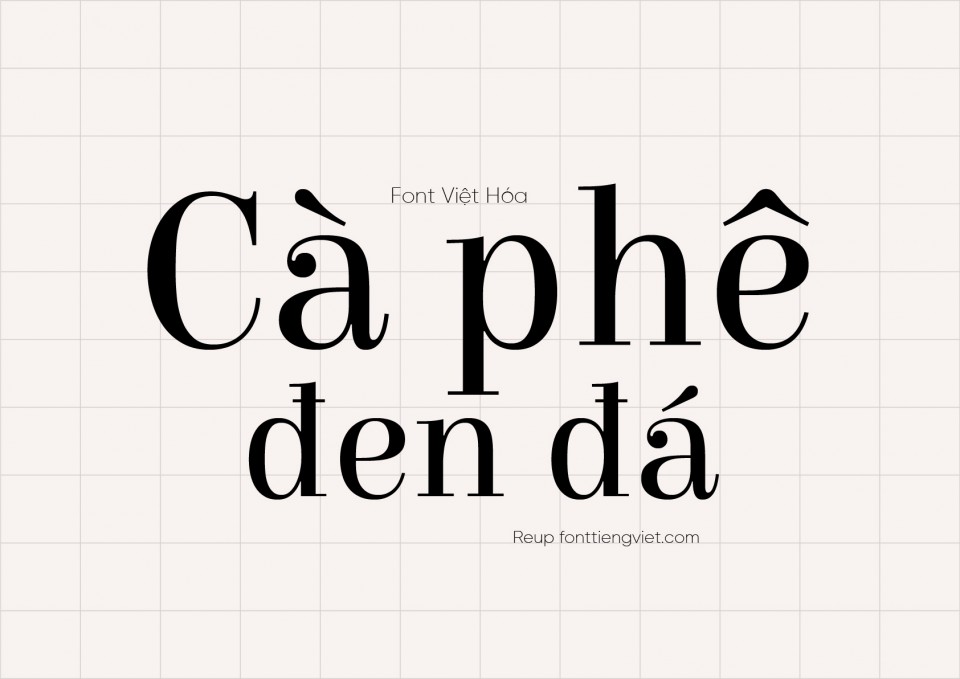
Tải Font việt hóa LNTH Elsie Miễn Phí Cho Thiết Kế Sáng Tạo
Giới thiệu về bộ Font việt hóa LNTH Elsie
Trong thế giới đồ họa hiện đại, việc lựa chọn một Font Chữ phù hợp đóng vai trò quan trọng trong việc truyền tải thông điệp. Font việt hóa LNTH Elsie là một tác phẩm nghệ thuật độc đáo, được thiết kế dành riêng cho những ai yêu thích sự mềm mại và tinh tế. Bộ font này không chỉ mang đậm nét nữ tính mà còn thể hiện sự sang trọng qua từng đường nét uốn lượn đặc trưng. Đối với các bạn học sinh và giáo viên, đây là lựa chọn tuyệt vời để làm mới các bài thuyết trình hay tài liệu học tập sinh động hơn.
Đặc điểm nổi bật của Font việt hóa LNTH Elsie
Thiết kế thanh lịch và bay bổng
Điểm ấn tượng nhất của Font việt hóa LNTH Elsie chính là sự kết hợp hoàn hảo giữa kiểu chữ Bodoni cổ điển và các chi tiết uốn lượn sáng tạo. Các ký tự được chăm chút tỉ mỉ, giúp tạo nên một tổng thể hài hòa và bắt mắt. Nhờ quá trình việt hóa chỉn chu từ đội ngũ LNTH, người dùng có thể hoàn toàn yên tâm sử dụng đầy đủ các dấu tiếng Việt mà không lo lỗi hiển thị. Điều này cực kỳ hữu ích khi thiết kế thiệp mời, bìa sách hoặc các tiêu đề trang trí trong môi trường học đường.
Ứng dụng đa dạng trong giáo dục
Dù mang phong cách nghệ thuật cao, Font việt hóa LNTH Elsie vẫn giữ được độ dễ đọc cần thiết. Bạn có thể sử dụng nó để trang trí báo tường, làm tiêu đề cho các dự án sáng tạo hoặc thiết kế các chứng nhận khen thưởng cho học sinh. Sự mềm mại của font chữ giúp giảm bớt sự khô khan của văn bản, từ đó kích thích sự hứng thú và khả năng sáng tạo của người xem.